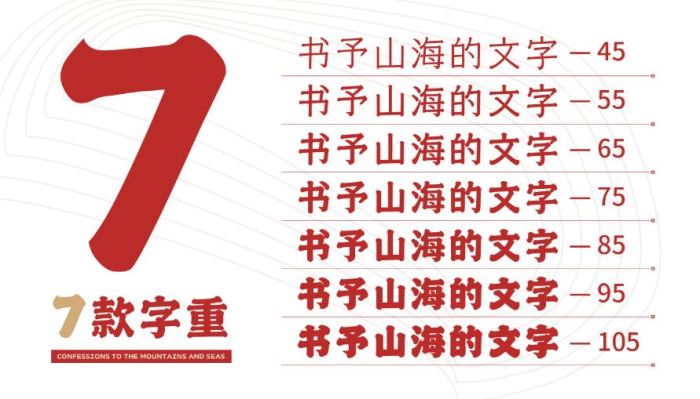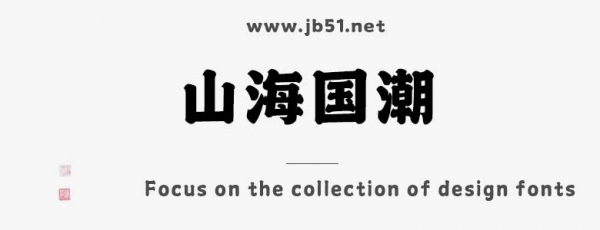
山海國(guó)潮家族是由山海字庫(kù)出品的字體,這款字體筆觸粗實(shí),字形端正,具有很好的視覺感,適合應(yīng)用于藝術(shù)設(shè)計(jì)、平面宣傳設(shè)計(jì)、網(wǎng)頁(yè)設(shè)計(jì),書法字帖等領(lǐng)域,需要的朋友可以前來本站下載。